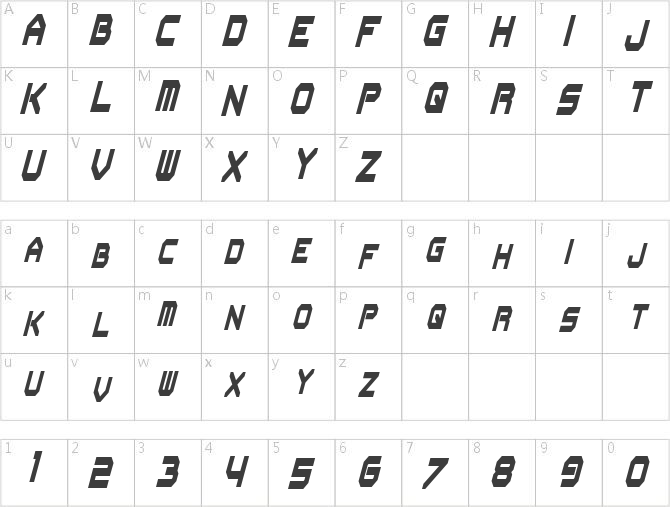
Flipbash Condensed Italic
Flipbash Condensed Italic介绍
Flipbash Condensed Italic字体字库是一款让人赏心悦目、百看不厌的英文字体,适合各类广告和产品包装设计应用,字体大小0.02MB,格式为ttf字体,上传用户是Me / ,yD ,作者/版权方为未知